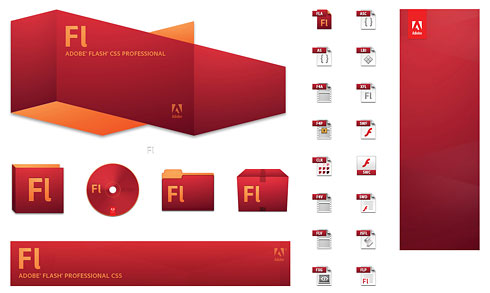
[Update] Danke für die Kommentare. Die belgische Designerin Veerle Pieters hat zwar eine Menge Insider-Wissen über die Konstruktion der Adobe-Brandings, sie ist allerdings nicht die Urheberin der Icons. Ich habe das im nachfolgenden Beitrag korrigiert.]
Grafikdesigner haben sie täglich vor Augen und klicken sie: Die Icons der berühmten Adobe-Programme InDesign, Photoshop, Illustrator, Flash und viele mehr. Die belgische Grafik- und Web-Designerin Veerle Pieters verfolgt seit Jahren die Veränderungen der Adobes-Creative-Suite-Icons -und der Begrüßungsfenster. Bereits 2006 stellt sie ausführlich dar, wie die einst naturalistisch angelegen Programmsymbole (Feder, Blume, Schmetterling …) entsorgt und durch farbige Flächen mit Abkürzungen ersetzt wurden, ähnlich eines Periodensystems (Fontblog berichtete: Was sagen uns die neuen Adobe-Icons).
Jetzt hat sie dem Leiter des Adobe Desktop Brand Teams, Shawn Cheris, erneut interessantes Entstehungsmaterial entlockt. In zwei reich bebilderten Blogbeiträgen berichtet Pieters ausführlich über die zweite Überarbeitung der typografischen con-Palette. Die Schöpfer berufen sich auf die Isometrik sowie die Farbgebung von Otl Aicher und erläutern, wie sie durch Farbe und Dimensionalität die Verdunkelungsgefahr minimiert haben. Die Reportagen sind spannend zu lesen und man ist erstaunt, wie umfangreich und vielfältig das Projekt angelegt ist:
Die Art wie die Formen abgeleitet werden finde ich sehr schön, die Schrift auf den Icons hätte man von mir aus auch gut dunkel lassen können, ich empfand das auf den farbigen Icons immer als angenehm ruhig.
Jep, für ein PSE (nicht „Photoshop Elements“!) geeignete Symbole, aber für Programme gehören sie immer noch zu den schlechtesten Icons aller Zeiten, die nur untereinander und so gar nicht mit anderen (inkl. Acrobat und OS) funktionieren wollen. Die Dateisymbole sind dagegen viel besser.
Kann mir jemand erklären warum das Bridge-Icon als einziges in der CS5 schwarz/dunkel beschriftet ist?
Eben weil es die “Bridge” ist die alle anderen Programme verknüpft? Das wäre mir dann aber etwas zu wenig markant.
Unglaublich, daß man zB in Illustrator die Richtung der Verläufe nicht einfach per Klick umdrehen kann, oder einer Outline einen Verlauf verpassen kann, was alles in InDesign möglich ist. Genauso blöd steht man da, wenn man nur einzelne Ecken eines Objektes abrunden will. Die “Free Distort” Funktion in Illustrator schaut immer noch so aus wie 1995. Das Farbmanagement ist auch immer noch lächerlich, weil man zB nicht einfach eine bestimmte Spot Color über die Palette mit einer anderen ersetzen kann, wie es in InDesign von Anfang an möglich war. Wenn wir schon dabei sind finde ich die Grafik-Engine in InDesign mies und immer noch viel zu langsam. :-) Wie hat Steve Jobs unlängst über Adobe gesagt? “They are lazy.” Sieht ganz so aus finde ich. (Ich verwende noch CS3… btw)